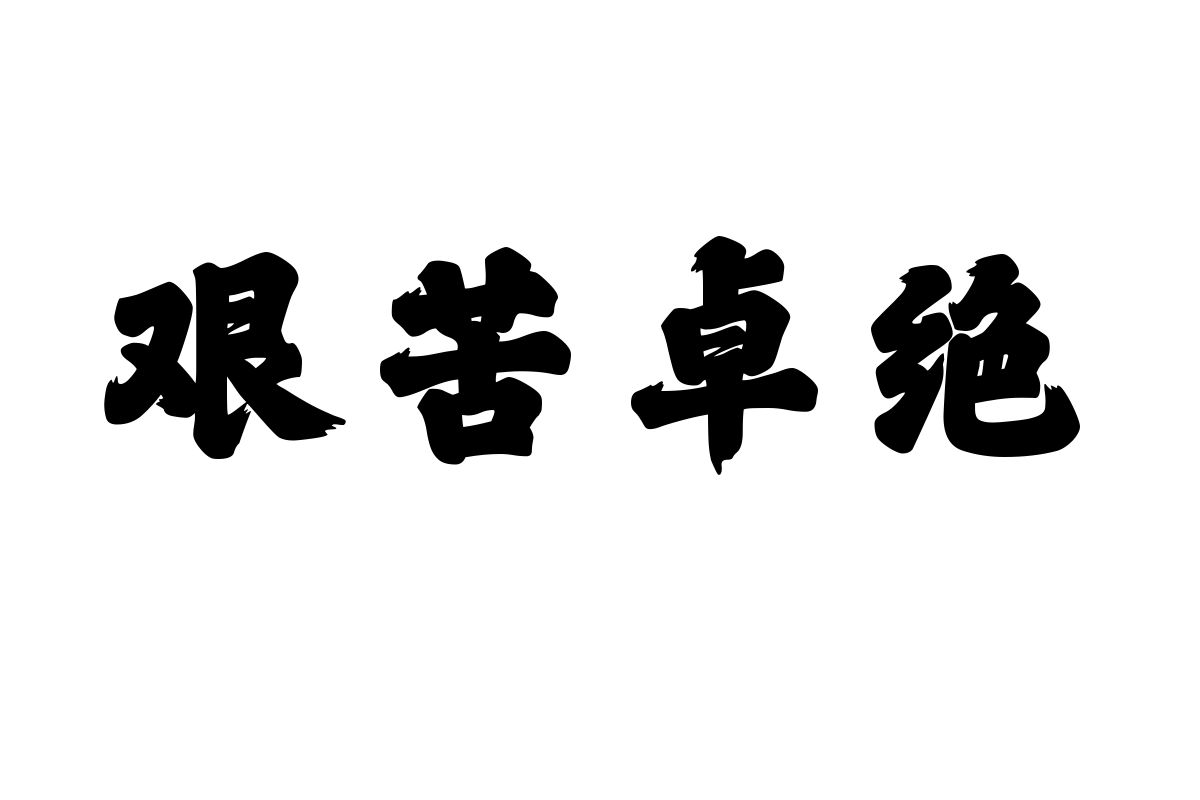
山海满江红w字体是一款具有独特风格的中文字体,由设计师精心打造。这款字体的特点在于其独特的字形结构和笔画流畅度,给人一种优雅、大气的感觉。
山海满江红w字体采用了传统的书法风格,将汉字的笔画进行了简化和优化。在保持原有书法韵味的同时,增加了一些现代元素,使得这款字体更加符合现代人的审美需求。
此外,山海满江红w字体还注重字体的可读性和易记性,使得人们在阅读时能够轻松识别和记忆。同时,该字体的适用范围广泛,无论是在广告设计、书籍封面、网页标题等场景中都能够发挥出良好的效果。
总之,山海满江红w字体是一款独具特色的中文字体,它既保留了传统书法的韵味,又融入了现代元素,能够满足不同场合的需求。